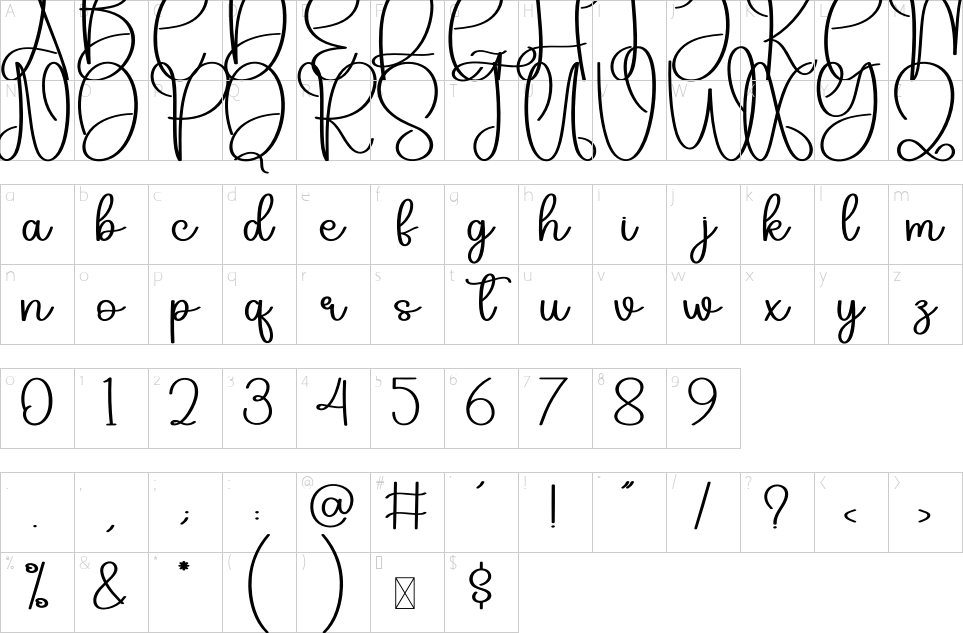
A fonte ‘Mother Day Font | 1001 Free Fonts’ é uma opção elegante e versátil para qualquer projeto de design gráfico. Desenvolvida por scratchones, esta fonte está disponível tanto para sistemas Windows quanto Mac. Com seus traços finos e elegantes, ela é perfeita para anúncios, cartas de aniversário e outros materiais que valorizam uma gráfica delicada. Com mais de 1000 fontes gratuitas disponíveis, a fonte ‘Mother Day Font’ é um excelente adicional para seu portfólio, especialmente durante esta data especial. Se você está procurando por uma fonte que não só é grata mas também lhe permite expandir sua paleta de fontes, ‘Mother Day Font’ é uma escolha certeira.